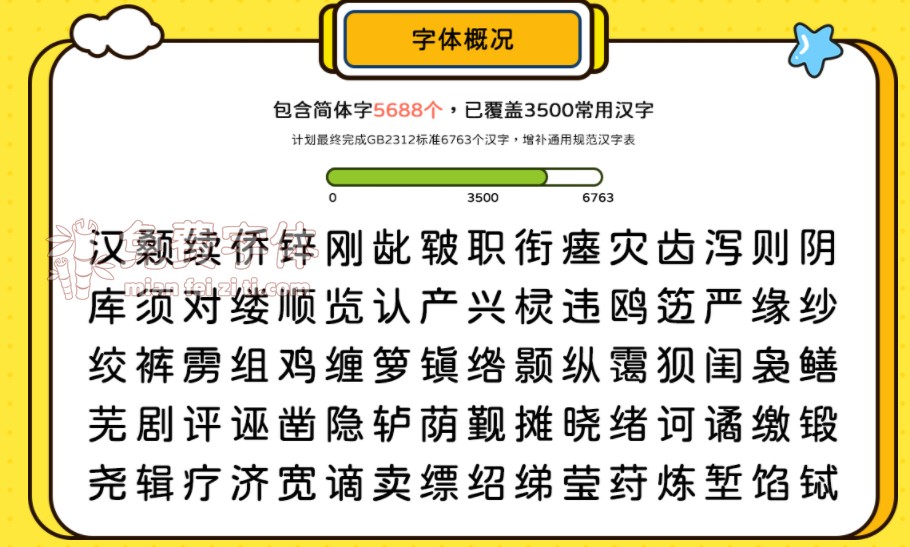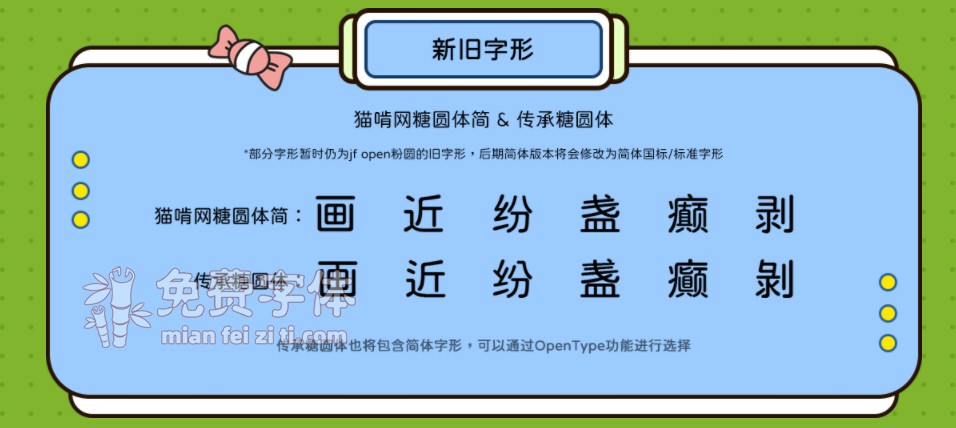
字体名称: 猫啃网糖圆体(测试版)
永久免费的糖圆体
小时候,我们总能被「一个简单的糖果」激发无限潜能,
创造力、好奇心,都是值得我们付出一生去珍藏的财富。
延续这一份童年的期待,长大后,我们对美味甜糖依旧无法自拔!
猫啃网糖圆体作为猫啃网首款免费商用字体
也许是起点,也许是终点,但是我依然希望Keep Moving……
关于猫啃网糖圆体的两个版本
糖圆体将会分为两个版本,一个是“猫啃网糖圆体”,这个版本将会以简体字体为主,在写法上会更贴近中国大陆的简体的习惯写法,现阶段准备发布的测试版本字体中许多字仍是旧字形,这些字将在完成gb2312的汉字后才会一并进行修改。
而另一个版本是“传承糖圆体”,这个版本主要由马来西亚的朋友@夜煞之乐进行维护。传承字形版本将会包含简体和繁体的字符集,在字形上以贴近原open粉圆的旧字形为主。另外,该字体也会通过OpenType功能提供简体版本的字形进行选择,但是在不支持OpenType的软件中仍会显示传承字形。
什么是传承字形(旧字形)?
传承字形(或称旧字形)是一个现行字形标准,虽然并未有规范硬性标准,但是在民间有一定的基础标准,也有民间组织为传承字形制定参考性标准。旧字形的来源符合字理字据,在一定程度上为不同来源的部件进行梳理分化,也考虑印刷字体的平衡感。传承字形最早来源可见于印刷铅字,现在繁体地区仍旧大量使用传承字形。
中国国家标准(简称国标)在1965年《印刷通用汉字字形表》中以楷体和俗体字为准,对宋体字形进行修订,也对其进行一定的笔画简省,让其符合一定的手写体标准。该标准作为一份强制性标准,完全覆盖了简化字与繁体字的印刷字形规范,并且造成一定程度上的字源流失与失衡。
在正文排版时,传承字形字体可以提供更加平衡、流畅及美观的视觉效果。本字体的传承字字形标准参考了原open粉圆的字形与民间传承字形组织「一点字坊」的《传承字形校检表》,而简化字部分的旧字形设计则参考了简体字制定新字形标准前的铅字字形进行设计。本字体作为一体扩展 (fork) 字体,在此选择使用旧字形进行一次大胆的尝试,保留原字体的断笔方式使其更加平衡,也保留了多数的旧字形特征以进行字源分化。另外,原字体部分汉字也在部件统一化时也一并修改,使其更加符合字源字理。
本字体的大陆设计师,@猫啃君将会在其「猫啃网糖圆体-简」中修改字形成新字形,@夜煞之乐也将配合他一起设计补充。目前部分汉字是有新字形的设计,但是在部件统一化时被替换了,在接下来的更新版本内会尽快提供异体选择,而当GB2312范围汉字完成时,「猫啃网糖圆体」将会分化成两个版本,即@猫啃君冠名的「猫啃网糖圆体-简」新字形版,与@夜煞之乐「传承糖圆体」版。